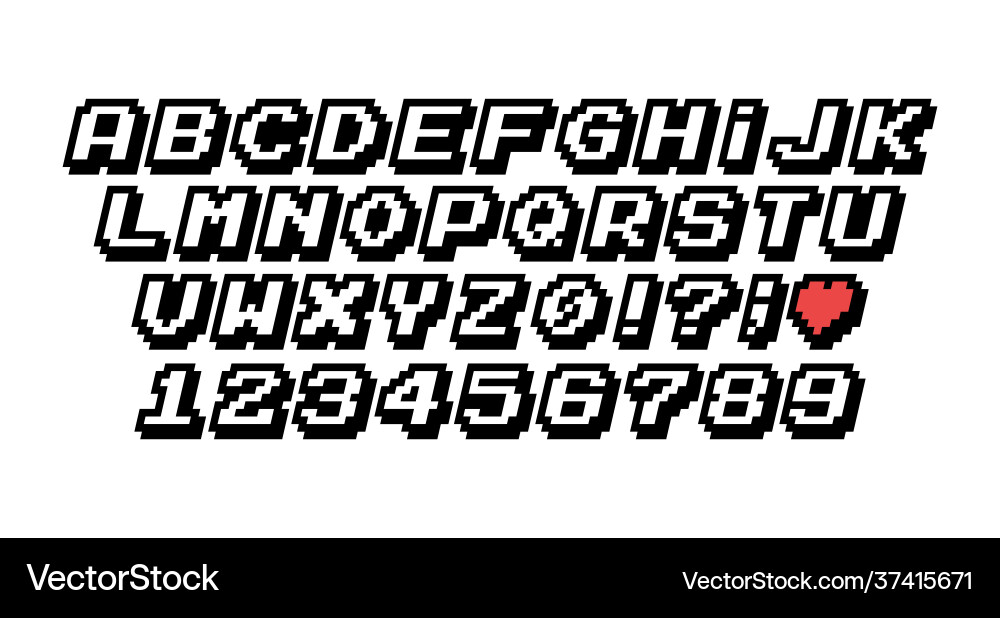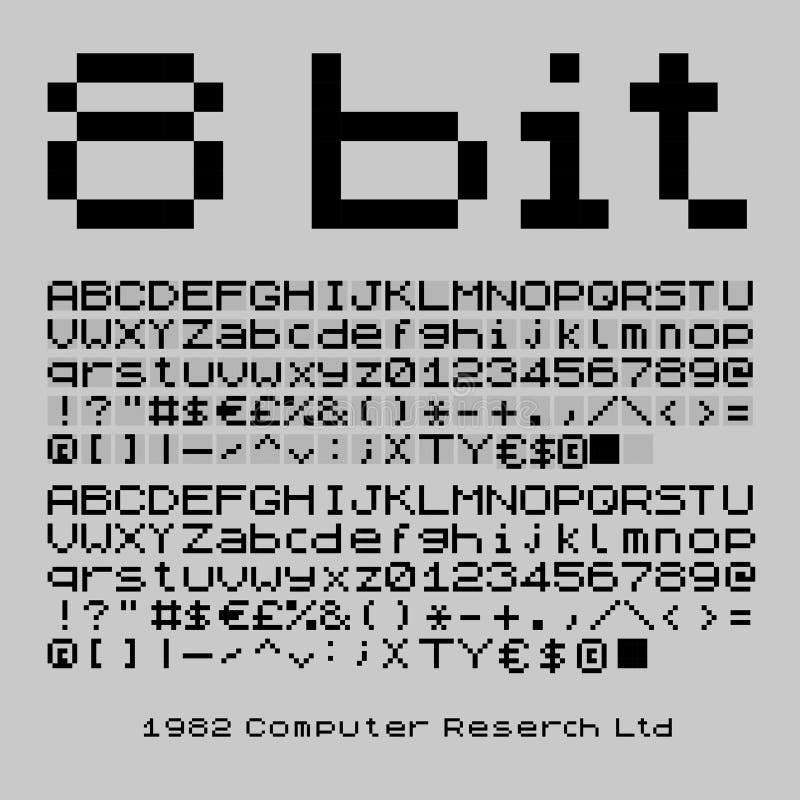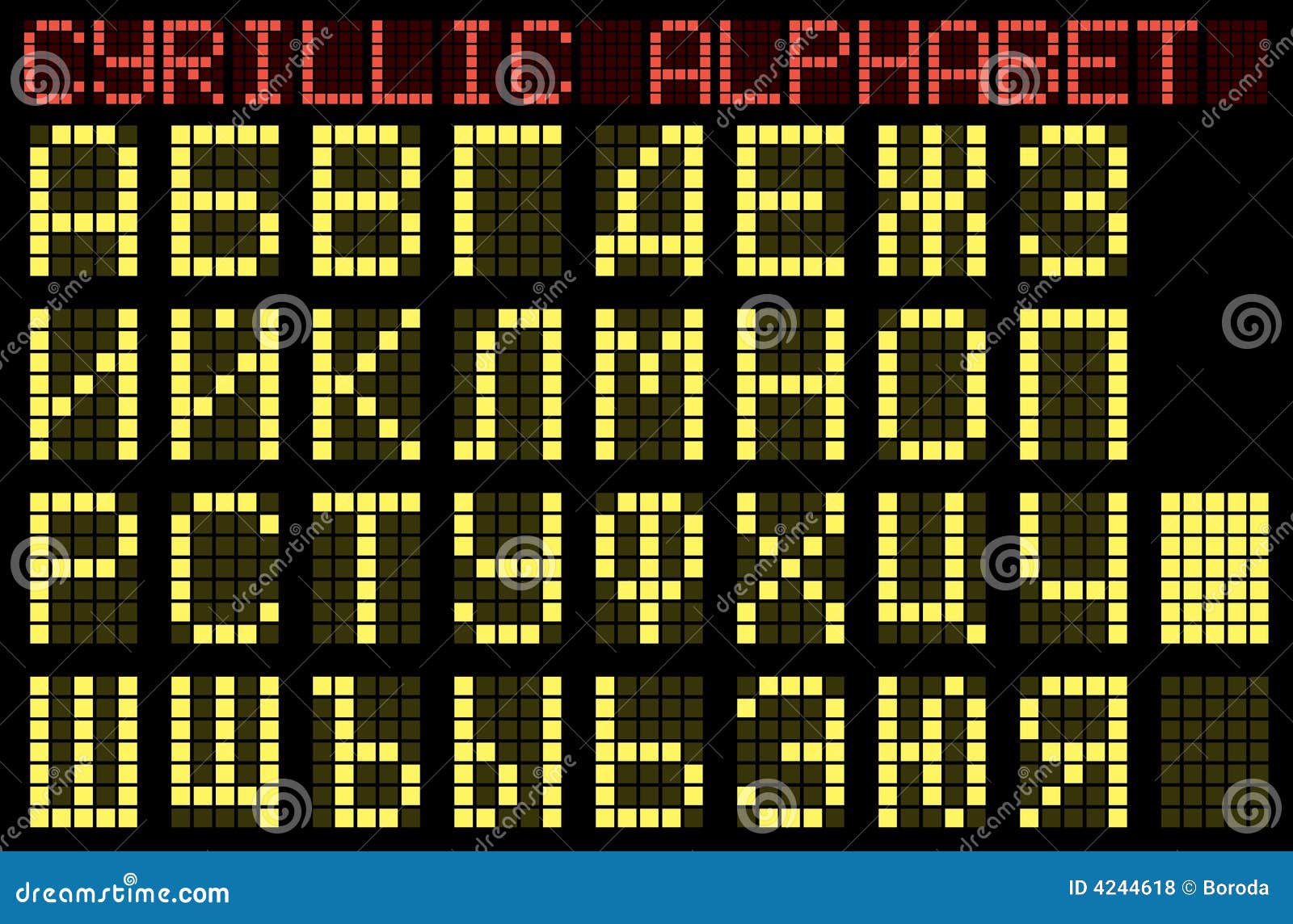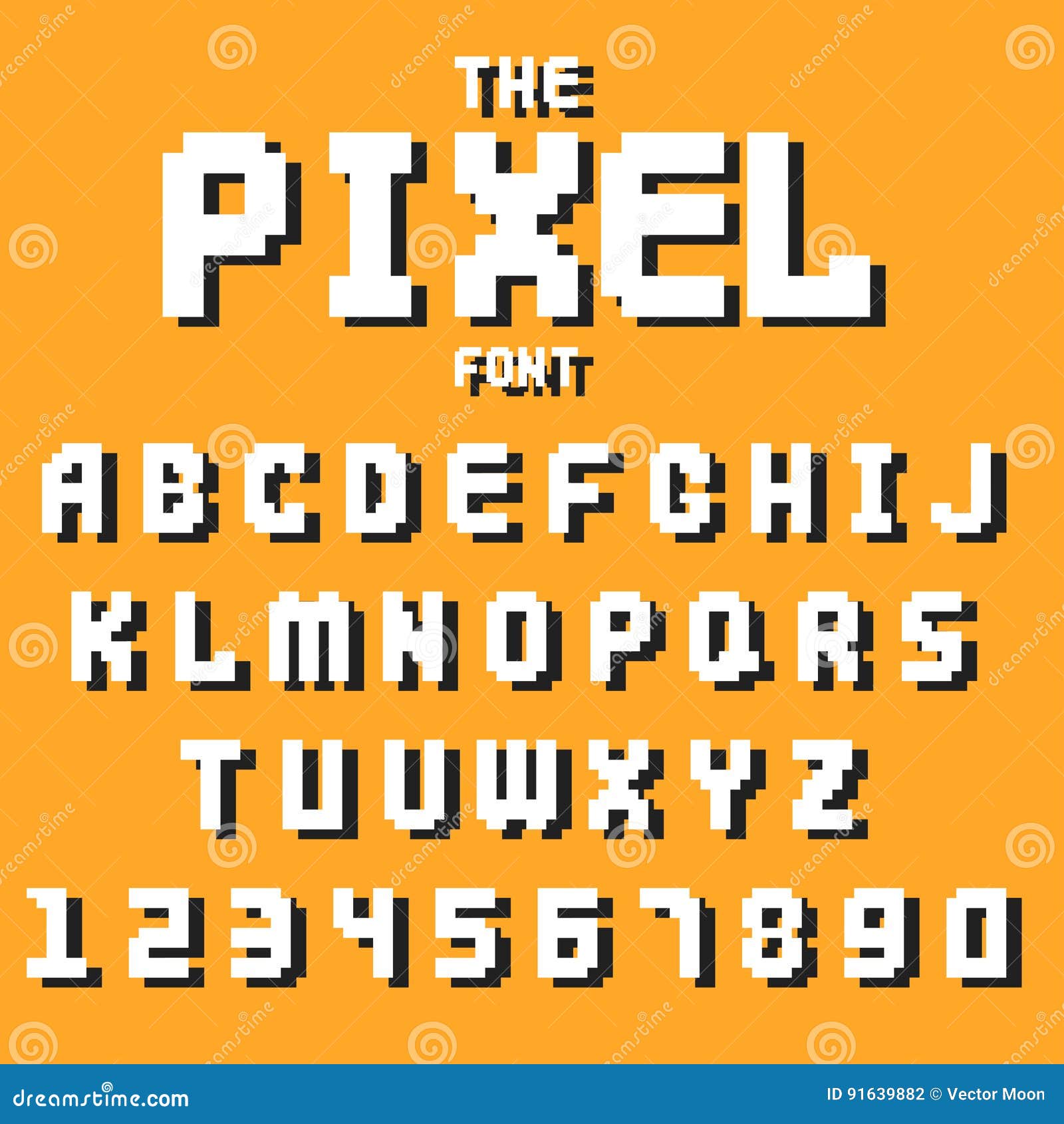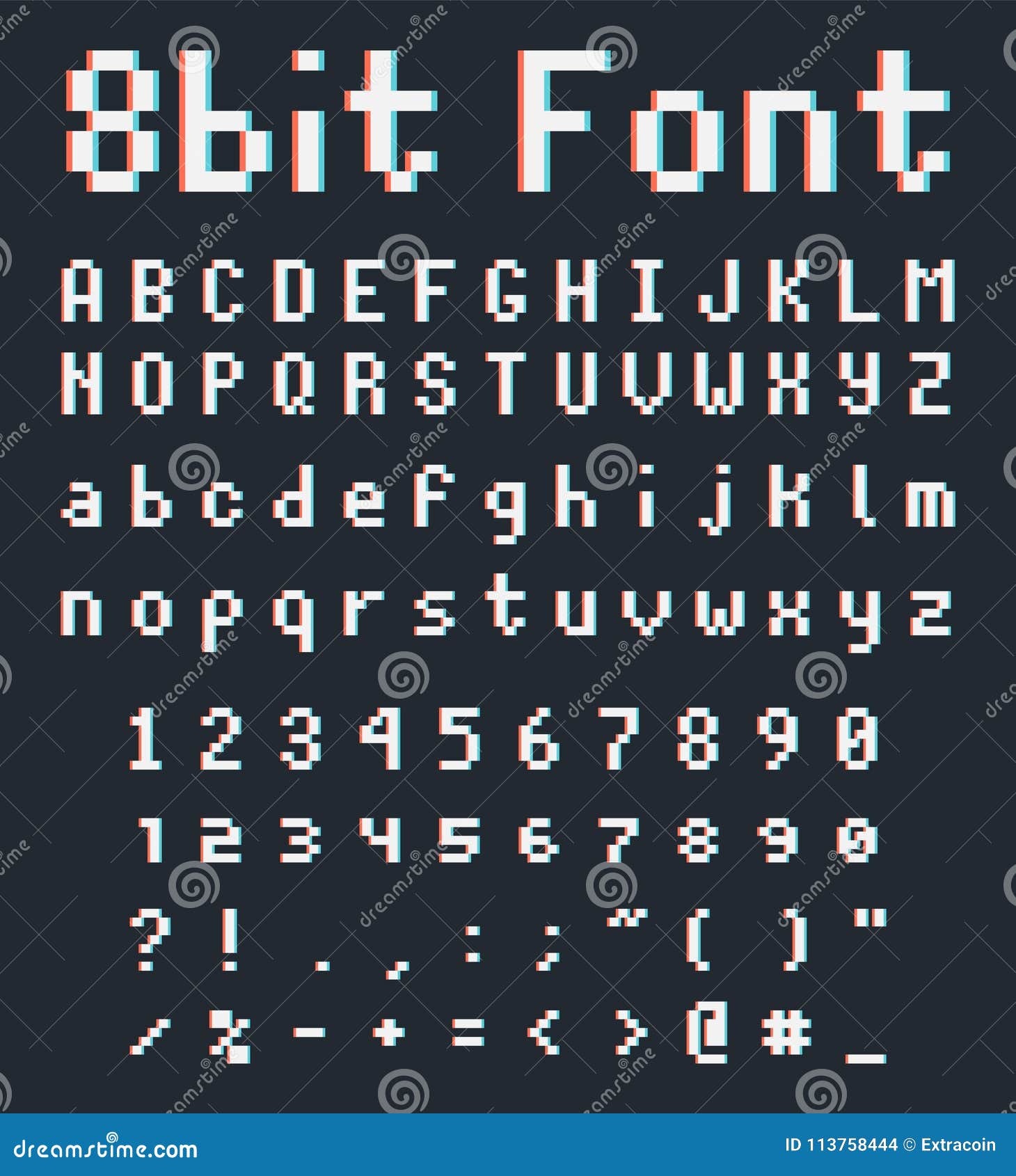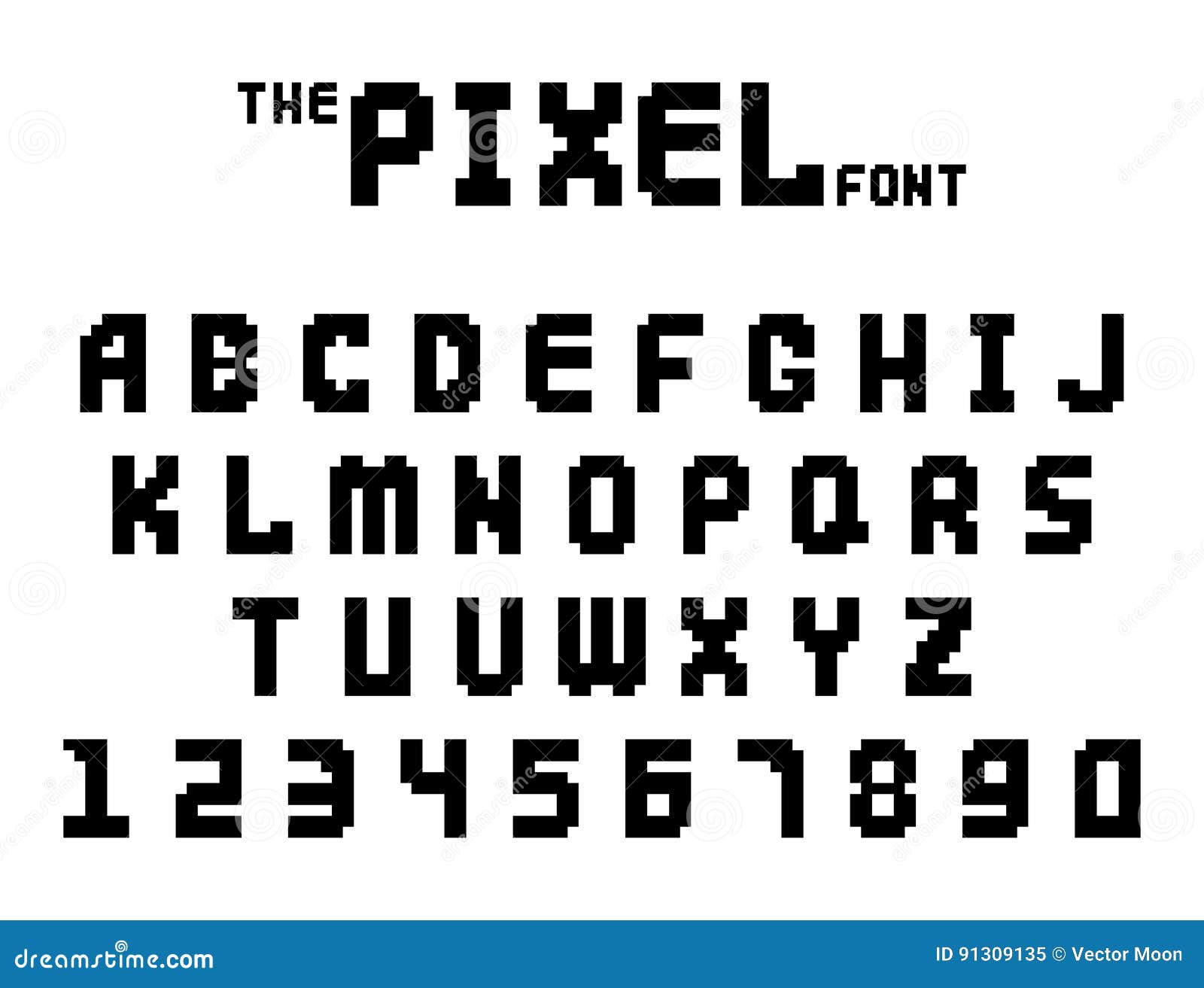
Пиксельные шрифты 8x16: оптимальные решения для ваших дизайнов и проектов
Пиксельные шрифты с размером 8x16 часто используются для создания ретро-эффекта и встраивания текста в проекты с ограниченными ресурсами. Они идеально подходят для старых игр, интерфейсов и проектов, ориентированных на ностальгию. В этой подборке мы рассмотрим лучшие примеры таких шрифтов, а также дадим советы по их правильному использованию, чтобы они идеально смотрелись на экране.
При использовании пиксельных шрифтов 8x16 важно помнить о том, что размер букв ограничен, и каждый пиксель имеет значение. Поэтому лучше всего использовать шрифты с максимальной читаемостью на небольших экранах.
Если ваш проект включает в себя графику с низким разрешением, выбирайте пиксельные шрифты, которые хорошо вписываются в общий стиль и сохраняют эстетичность даже при масштабировании.
Не забывайте проверять контрастность между фоном и текстом. Шрифты 8x16 могут выглядеть плохо при низком контрасте, поэтому стоит выбирать четкие и яркие цвета для текста.
Используйте ограниченную палитру цветов для пиксельных шрифтов, чтобы сохранить гармонию и не перегрузить визуальную часть проекта. Простые цвета лучше всего подходят для такого рода шрифтов.
При проектировании интерфейсов с пиксельными шрифтами 8x16 учитывайте, что они могут быть сложными для чтения на устройствах с низким разрешением. Рекомендуется тестировать шрифты на различных экранах, чтобы удостовериться в их читаемости.
Не забывайте про отступы между буквами и строками. Пиксельные шрифты могут выглядеть нечеткими или сливать символы, если отступы слишком малы. Подберите оптимальное расстояние для лучшего восприятия.
Если вы работаете над проектом с текстами на разных языках, учитывайте особенности использования пиксельных шрифтов 8x16 для других алфавитов, например, кириллицы или арабского письма.
Для улучшения читаемости на мобильных устройствах уменьшайте размер шрифта в зависимости от разрешения экрана, чтобы текст не терял четкость.
Если вы хотите сохранить эффект пиксель-арт, не перегружайте шрифт лишними деталями. Чем проще и лаконичнее шрифт, тем более эффектным будет его использование.
Не забывайте, что для создания ретро-стиля пиксельный шрифт должен гармонично сочетаться с остальной графикой, включая спрайты и фоны, чтобы создать единую визуальную атмосферу.